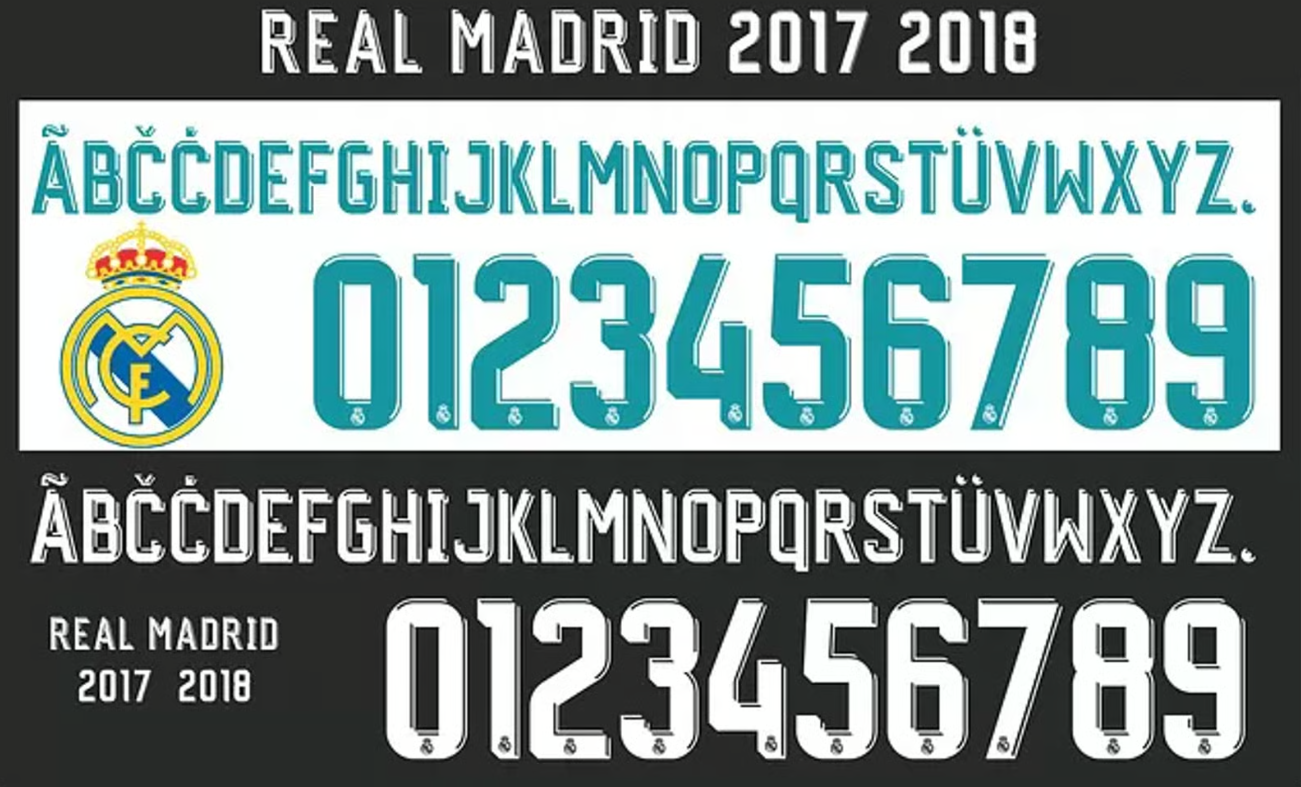
Reviva uma das épocas mais vitoriosas da história dos Merengues. A temporada 2017/2018 não marcou apenas mais uma conquista da Europa pelo Real Madrid, mas também trouxe um dos kits mais elegantes produzidos pela Adidas.
Neste post, você tem acesso ao download da fonte oficial utilizada na camisa titular (branca com detalhes em azul turquesa) e na camisa reserva (preta), vestidas por lendas como Cristiano Ronaldo, Sergio Ramos e Luka Modrić. É o arquivo perfeito para quem busca fidelidade histórica na personalização.
Estilo Visual e Aplicação
A tipografia desenvolvida pela Adidas para esta temporada do Real Madrid rompeu com o tradicionalismo. Com um visual moderno e ligeiramente futurista, a fonte se destaca pelos seus cortes diagonais e ângulos agudos, criando uma sensação de movimento e velocidade.
Diferente das fontes arredondadas de anos anteriores, este estilo geométrico “tech” conversa perfeitamente com o tom azul turquesa (teal) escolhido para os detalhes daquele ano.
É uma fonte que transmite a agressividade e a precisão do time que dominou o mundo. Ideal para estampar réplicas de camisas retrô, criar banners de “Dia de Jogo” ou produzir mockups de alta qualidade.
Dica de Design: Ao utilizar esta fonte, atenção ao espaçamento reduzido entre os números, uma característica marcante da aplicação oficial da La Liga e da Champions League naquela temporada.